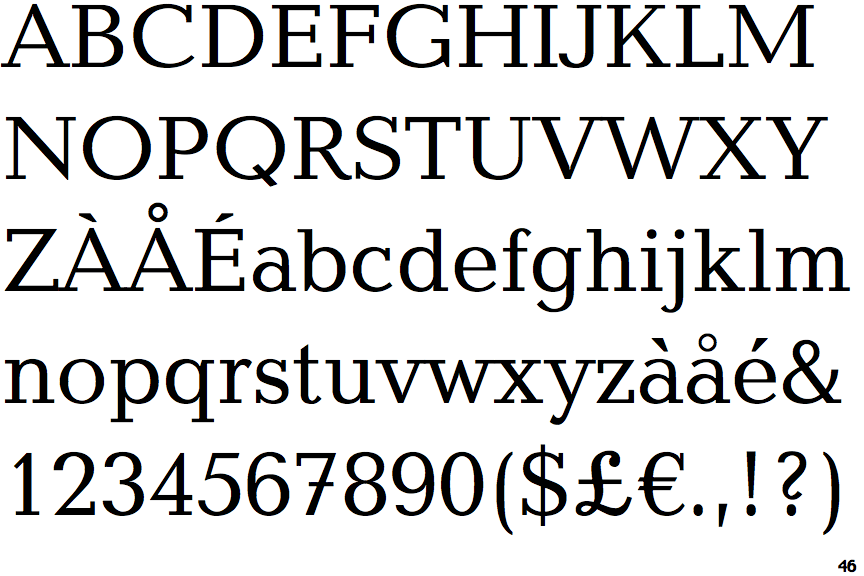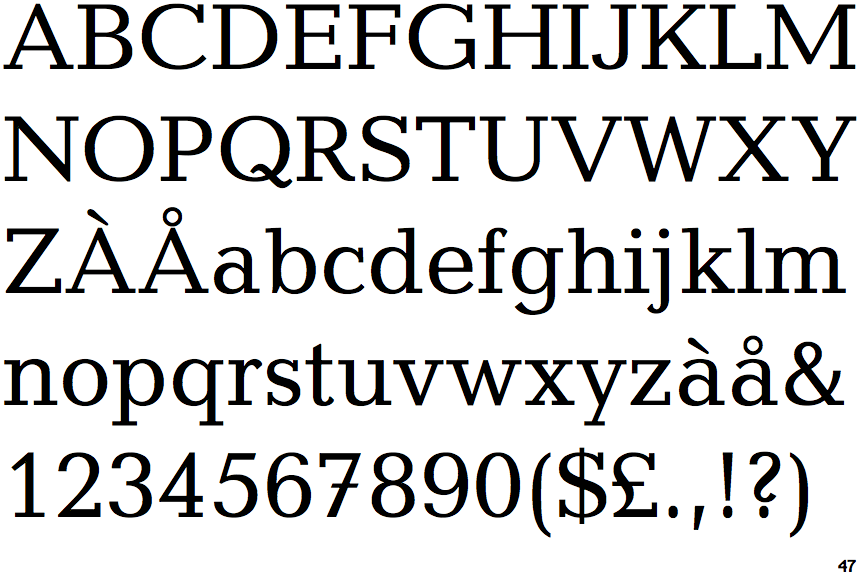
BT-Drucks. bis 1996 (Schriftart der Bundestags-Drucksachen jahrzehntelang bis zum Jahre 1996)
Hier eine völlig beliebige Bundestags-Drucksache (BT-Drucks.) aus dem Jahre 1996 (ganz beliebig dann doch nicht, denn darin finden sich alle drei Schriftschnitte normal/fett/kursiv gleich auf der ersten Seite):
Weiß jemand, welche Schriftart das ist? Gibt es die heutzutage überhaupt noch in digitalisierter Form? Mir gefällt sie nämlich sehr gut.
Diese Schrift findet sich jahrzehntelang in allen BT-Drucks. mindestens bis zum Jahre 1996; spätestens ab 2000 werden dann andere Schriften verwendet (Times New Roman, Arial).
schau mal auf die Schriften Candida und Baltica. Das geht in diese Richtung.
Typeface:	Candida
Designer:	Jakob Erbar
Year:		1936, 1989
Publishers:	Adobe and Linotype
Influence on:	Baltica
Originally designed by Jakob Erbar for
Ludwig & Mayer in 1936.
Typeface:	Baltica
Designer:	Vera Chiminova, Isay Slutsker and Alexander Tarbeev
Year:		1951-2,1988
Publisher:	ParaType
Influenced by:	Candida
Originally designed at Polygraphmash in 1951-52 by
Vera Chiminova, Isay Slutsker, et al.